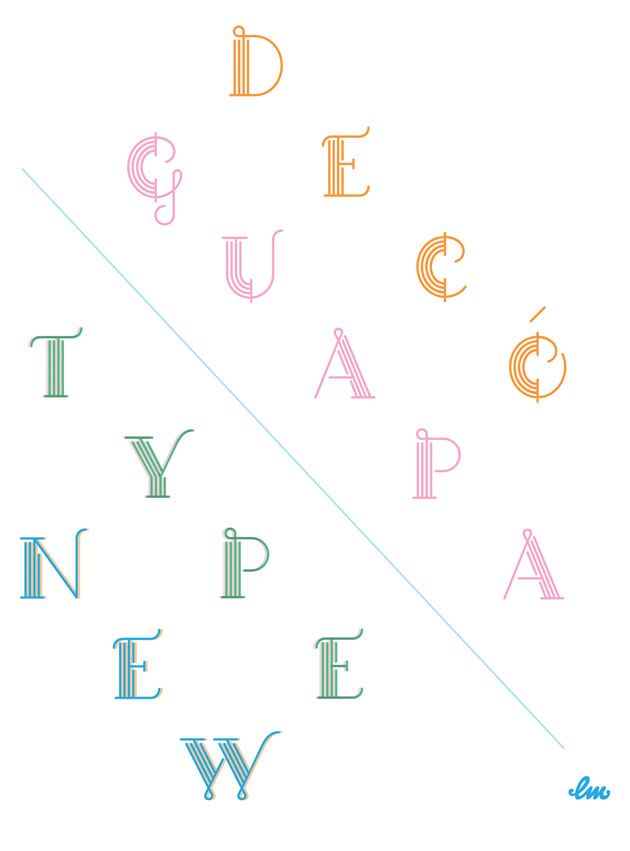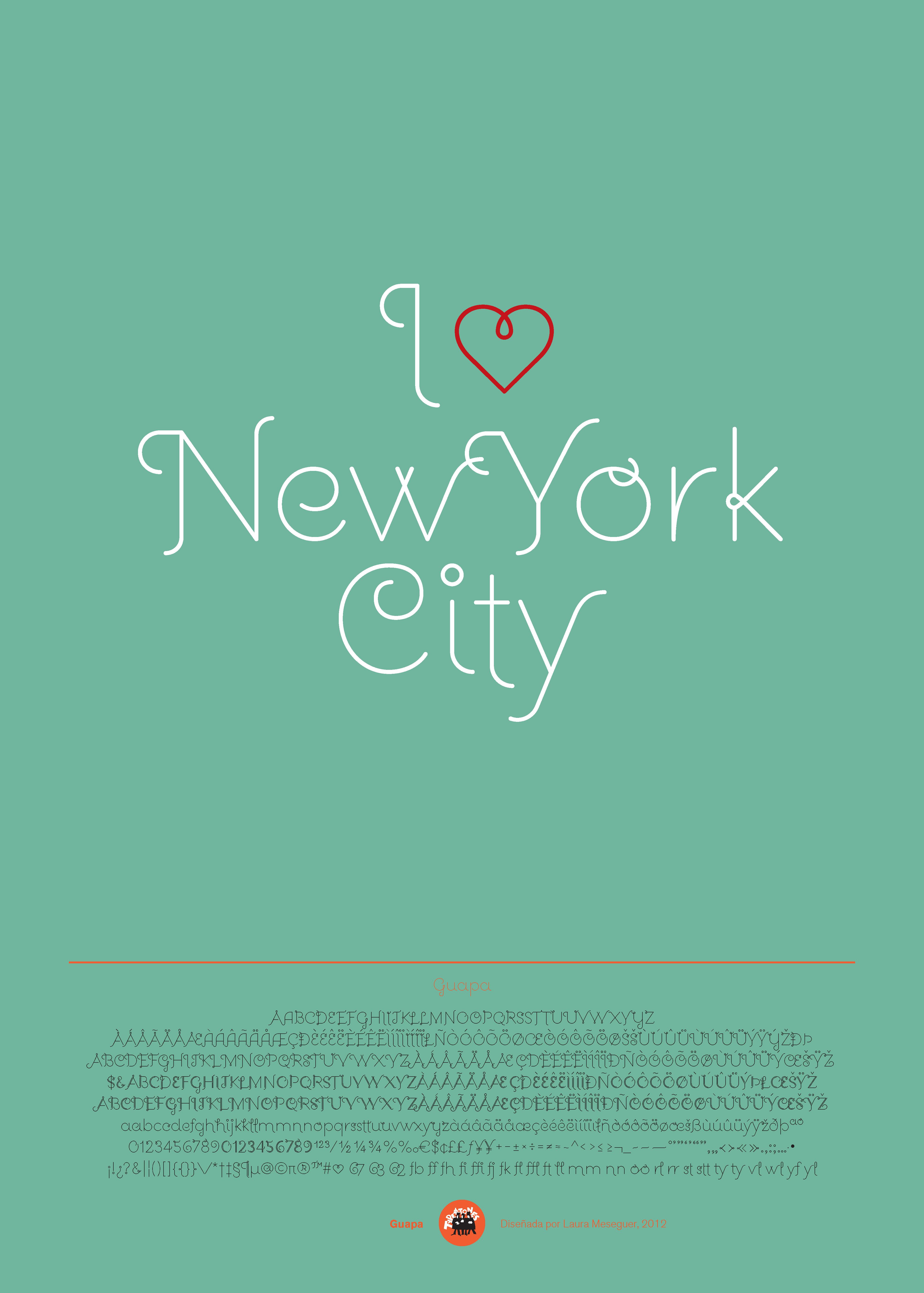
Guapa, una tipografía sans serif decorada
por Laura Meseguer @laura-meseguer
Guapa surgió de un experimento personal: la transformación de una sans serif geométrica "a la Futura" en un diseño Decó postmoderno y encantador. Nació para el diseño de un cartel para la exposición de tipografía "Pimp the type", celebrada primero en Barcelona y después en el 6ct Congreso de tipografía de Valencia. Inicialmente consistía en un solo peso, provisto de ligaduras de dos y tres caracteres, caracteres alternativos e iniciales. Después Laura diseñó GuapaDecó, que es un poco más experimental.
Diseñada por Laura Meseguer, 2012. Disponible en Type-Ø-Tones.